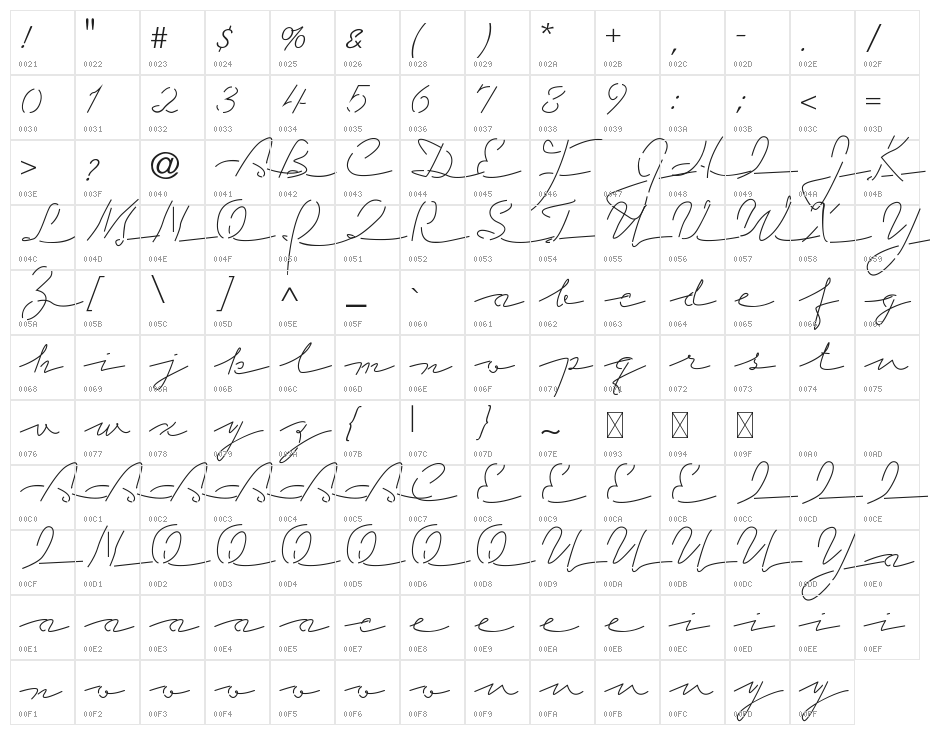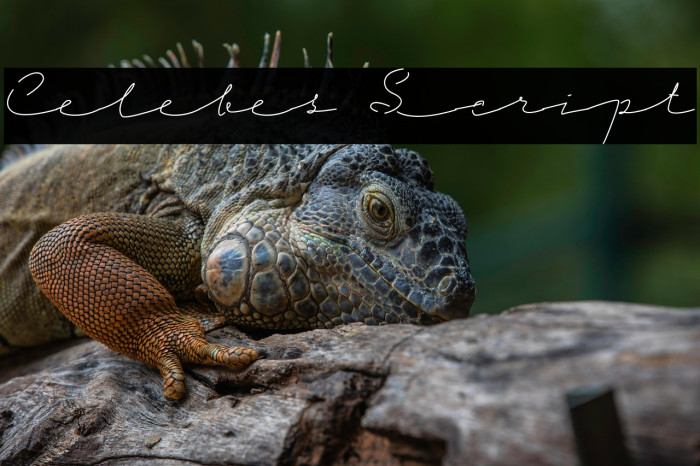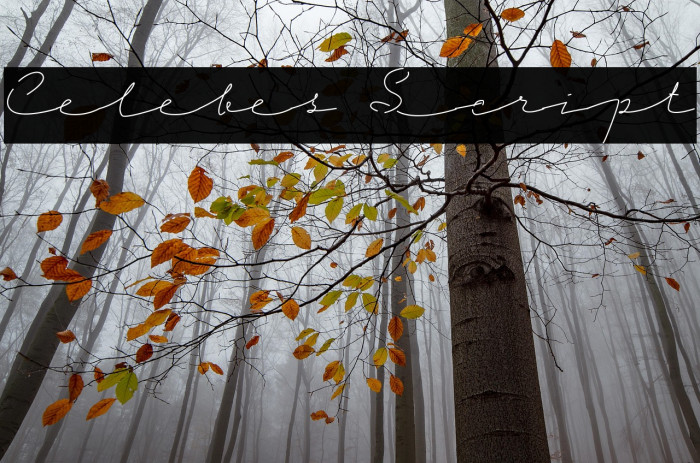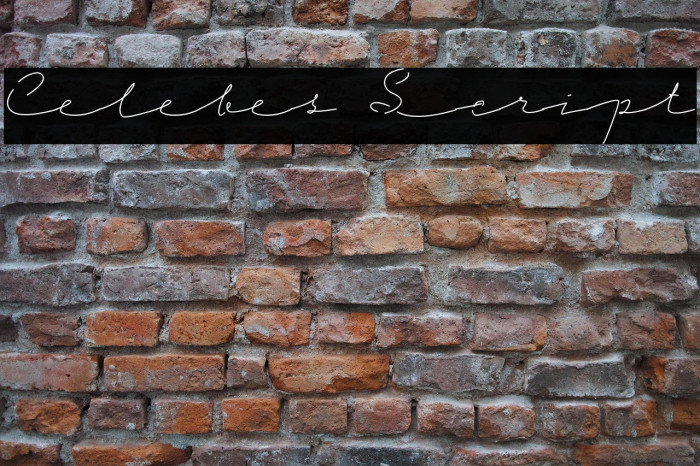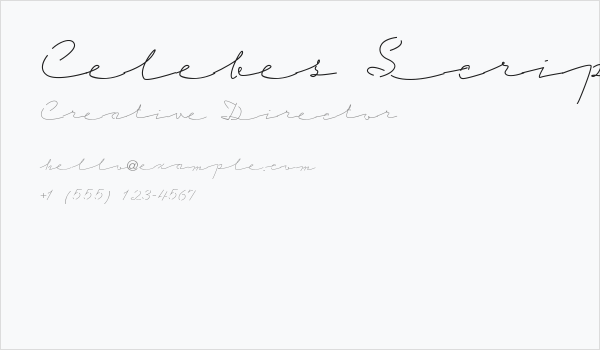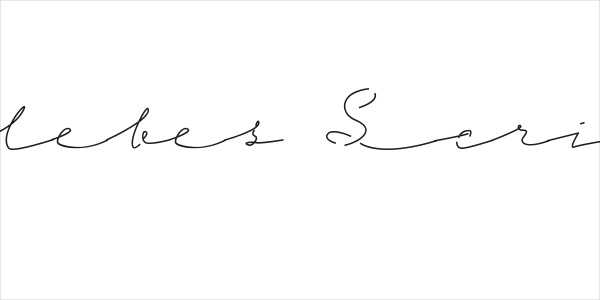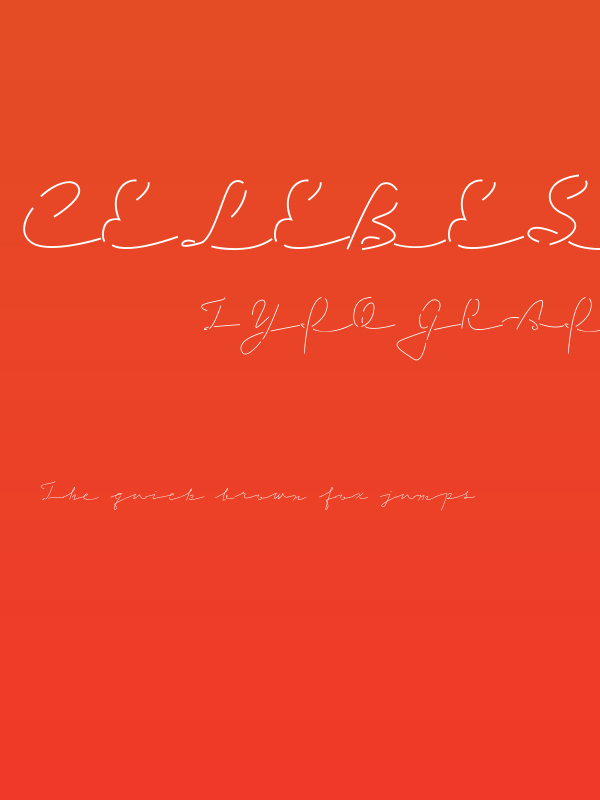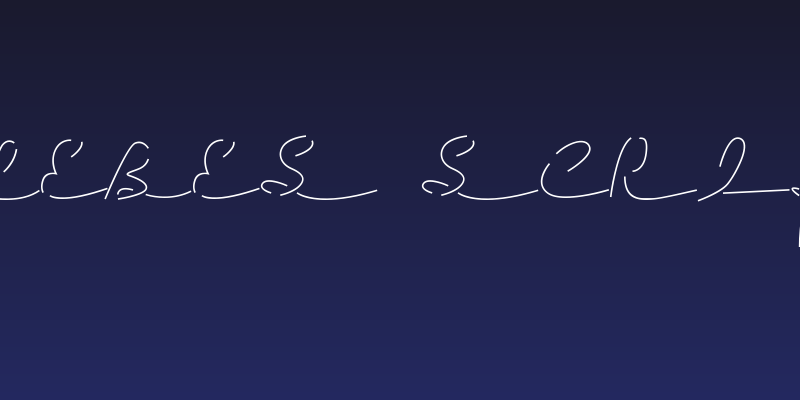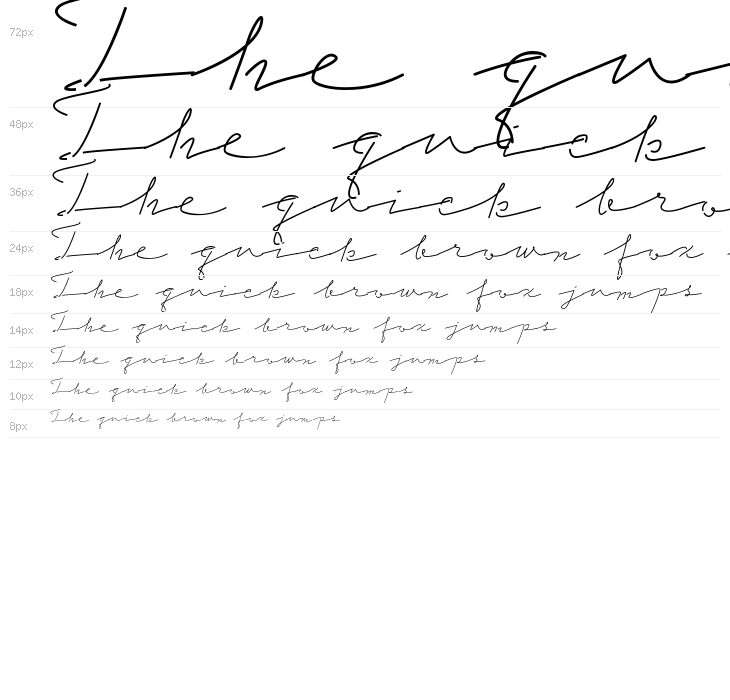
Celebes Script Font
| Stile generale | Elegant, Handwritten |
| Caso d'uso | Logos, Invitations, Personal Correspondence |
| Progetti proposti | Ideal for wedding invitations, personal letters, branding projects, and elegant stationery. |